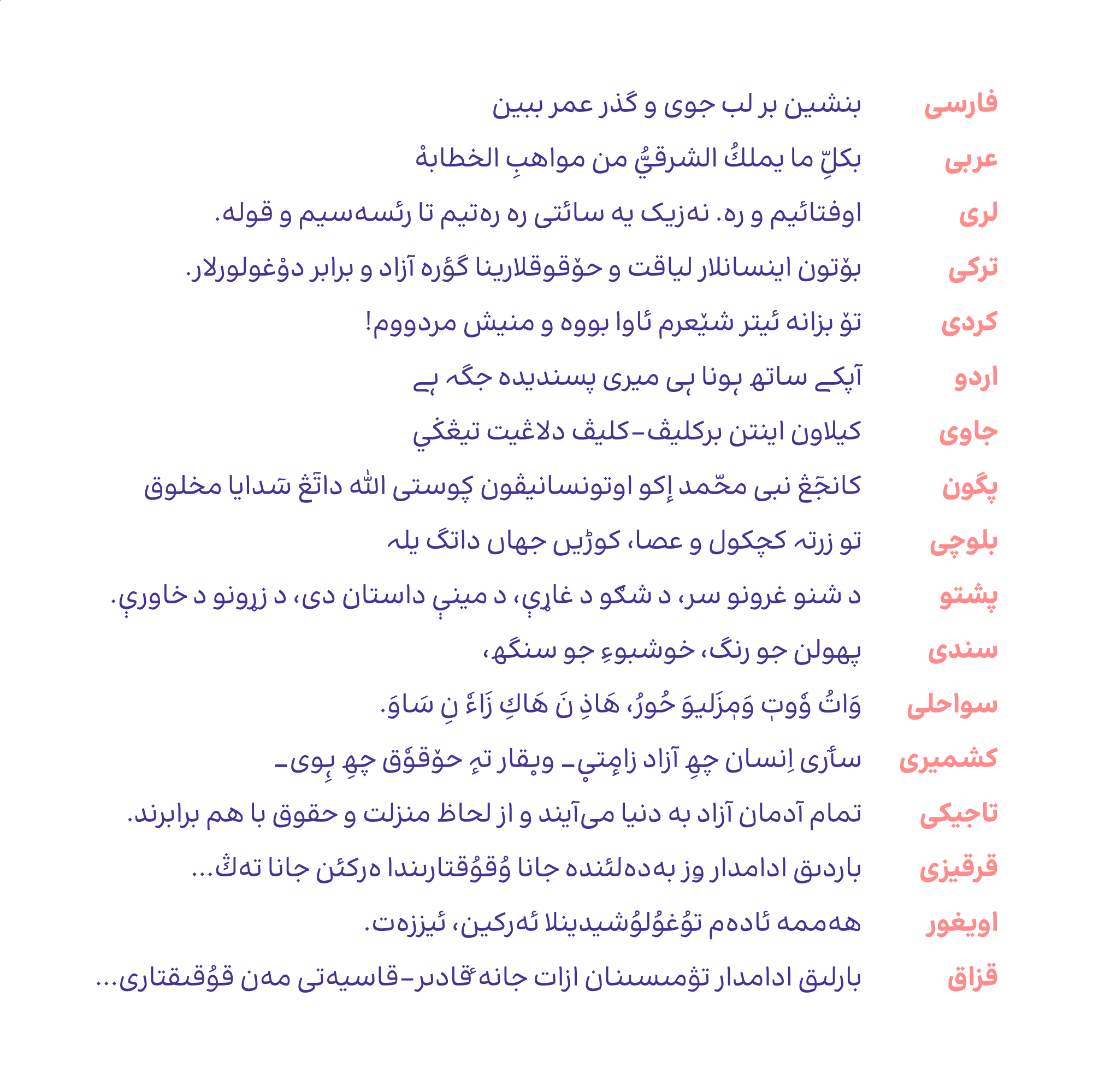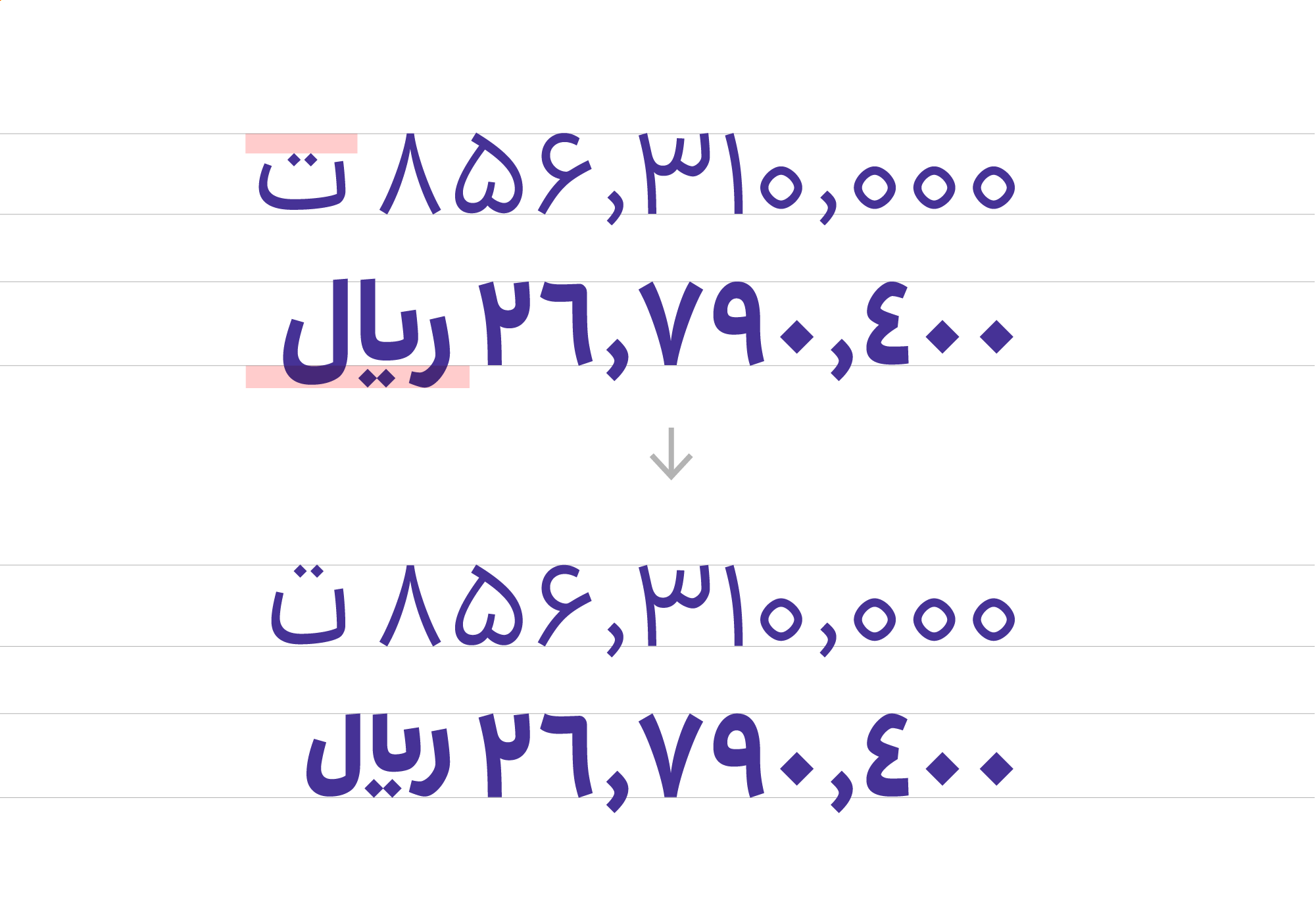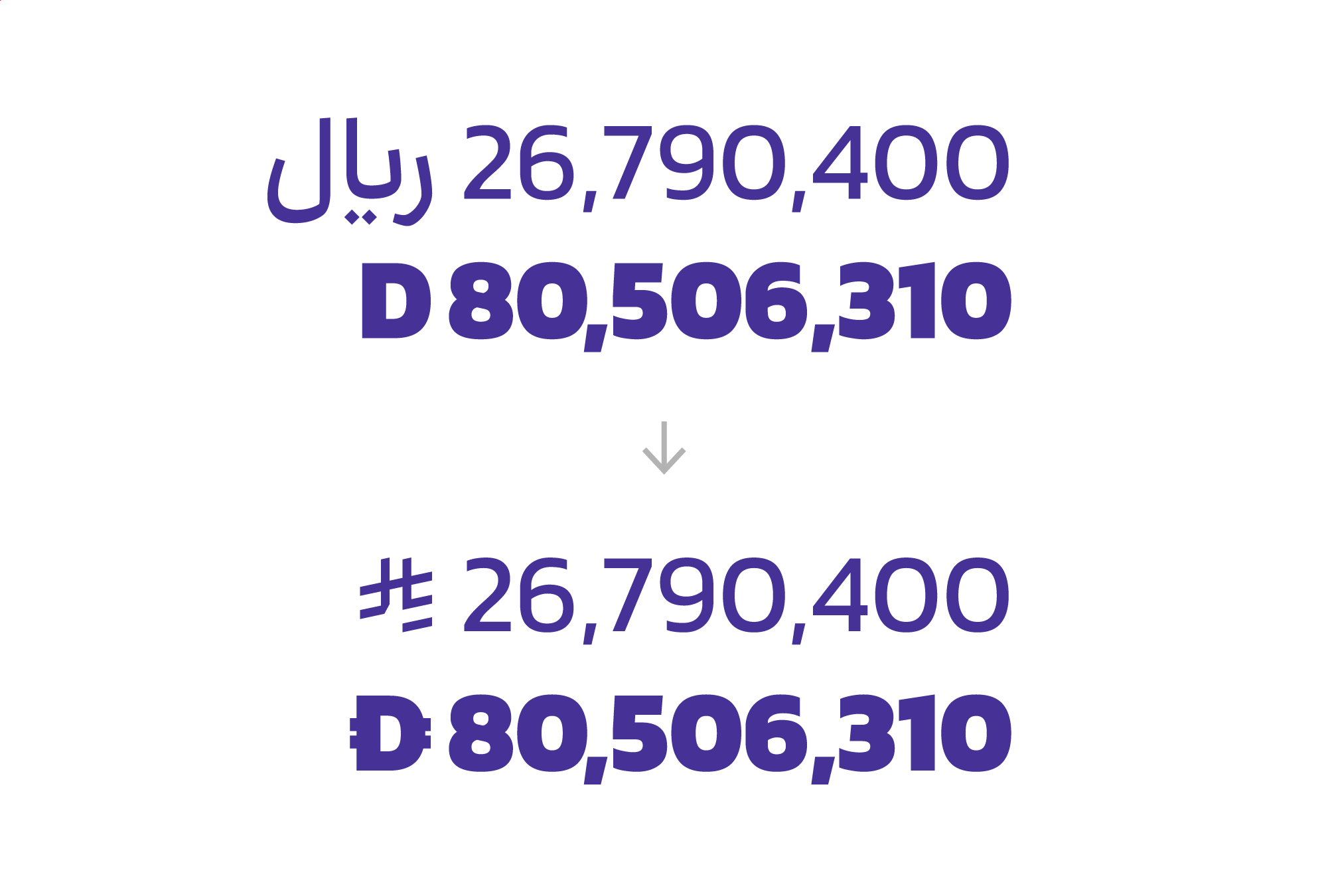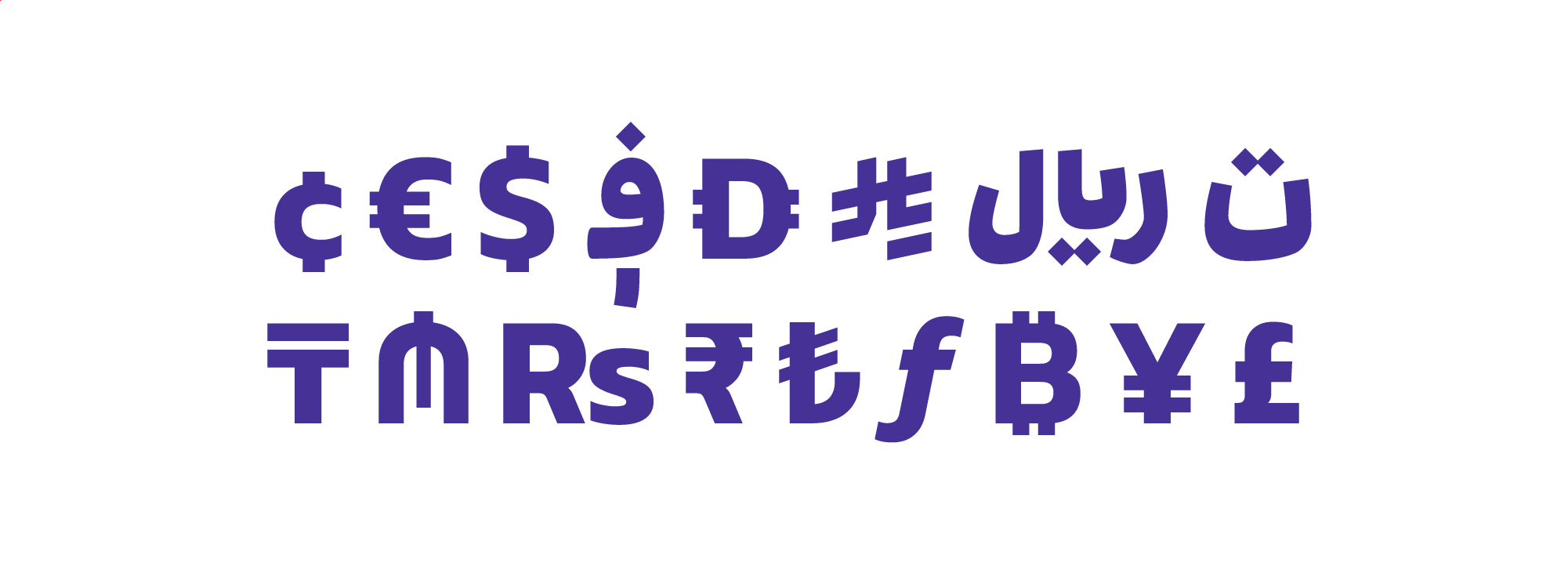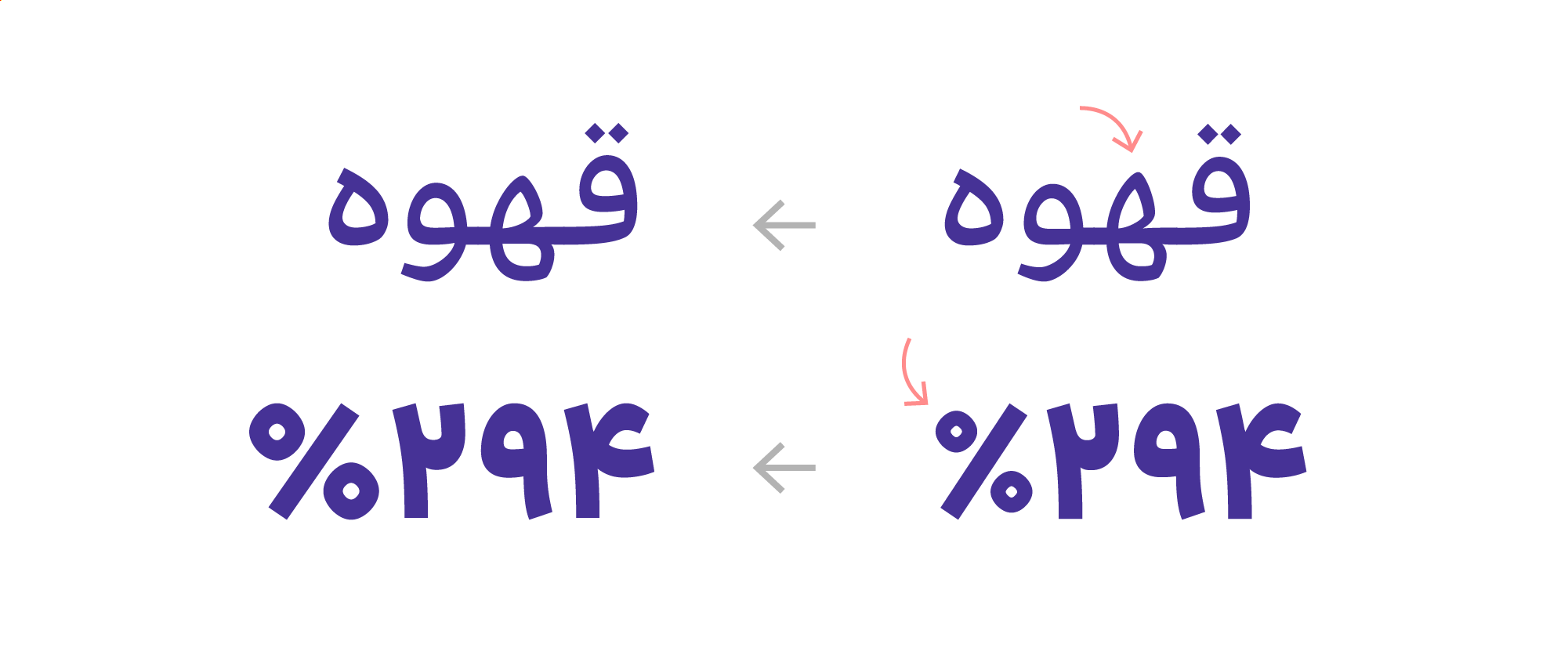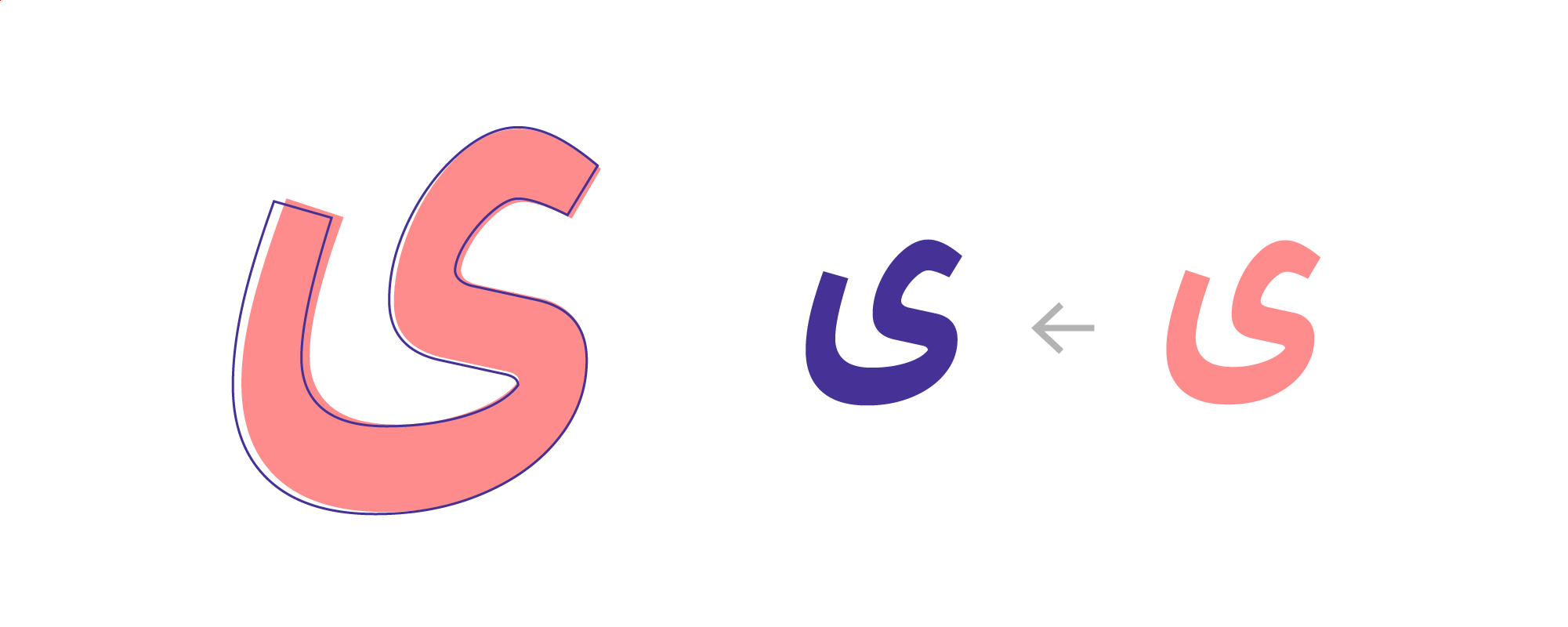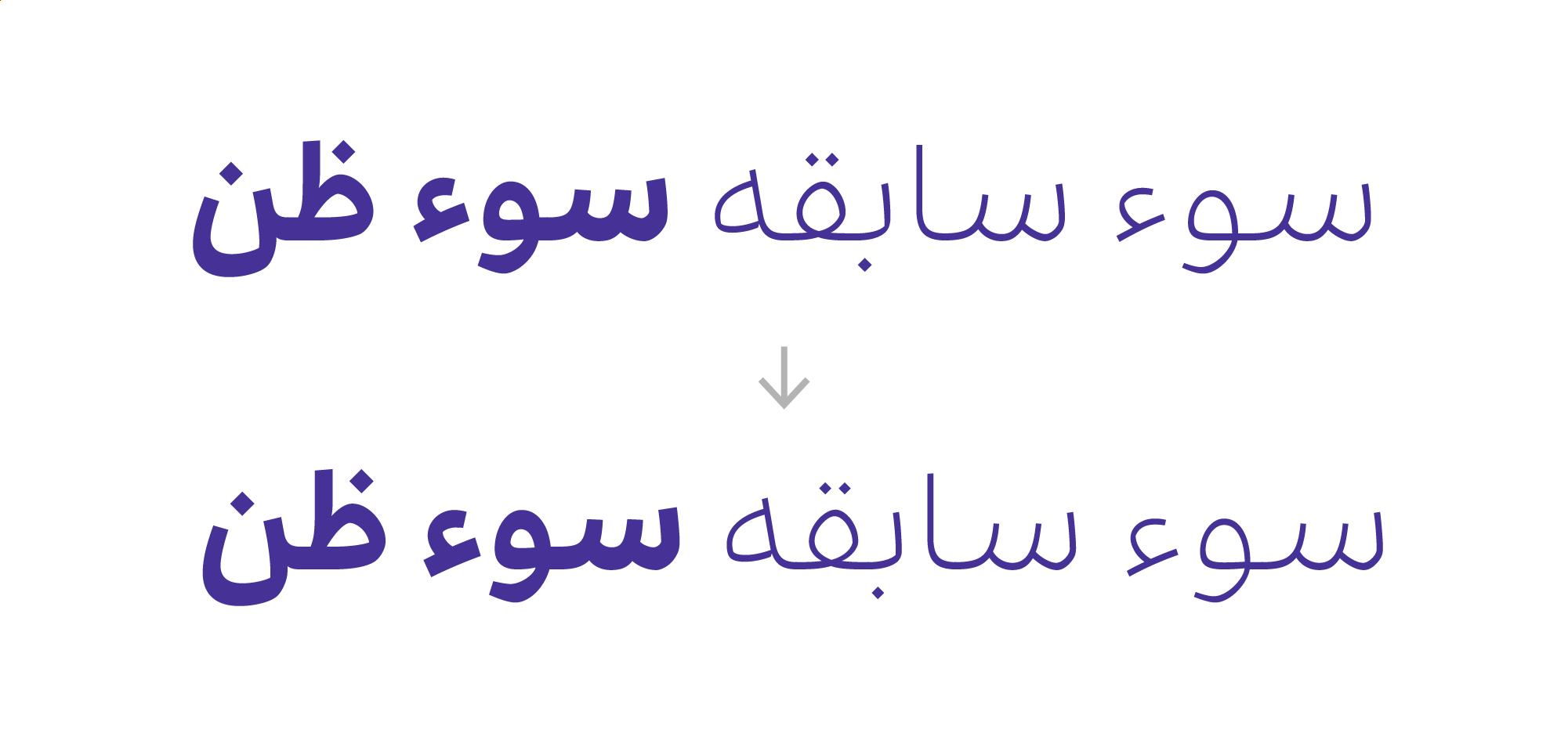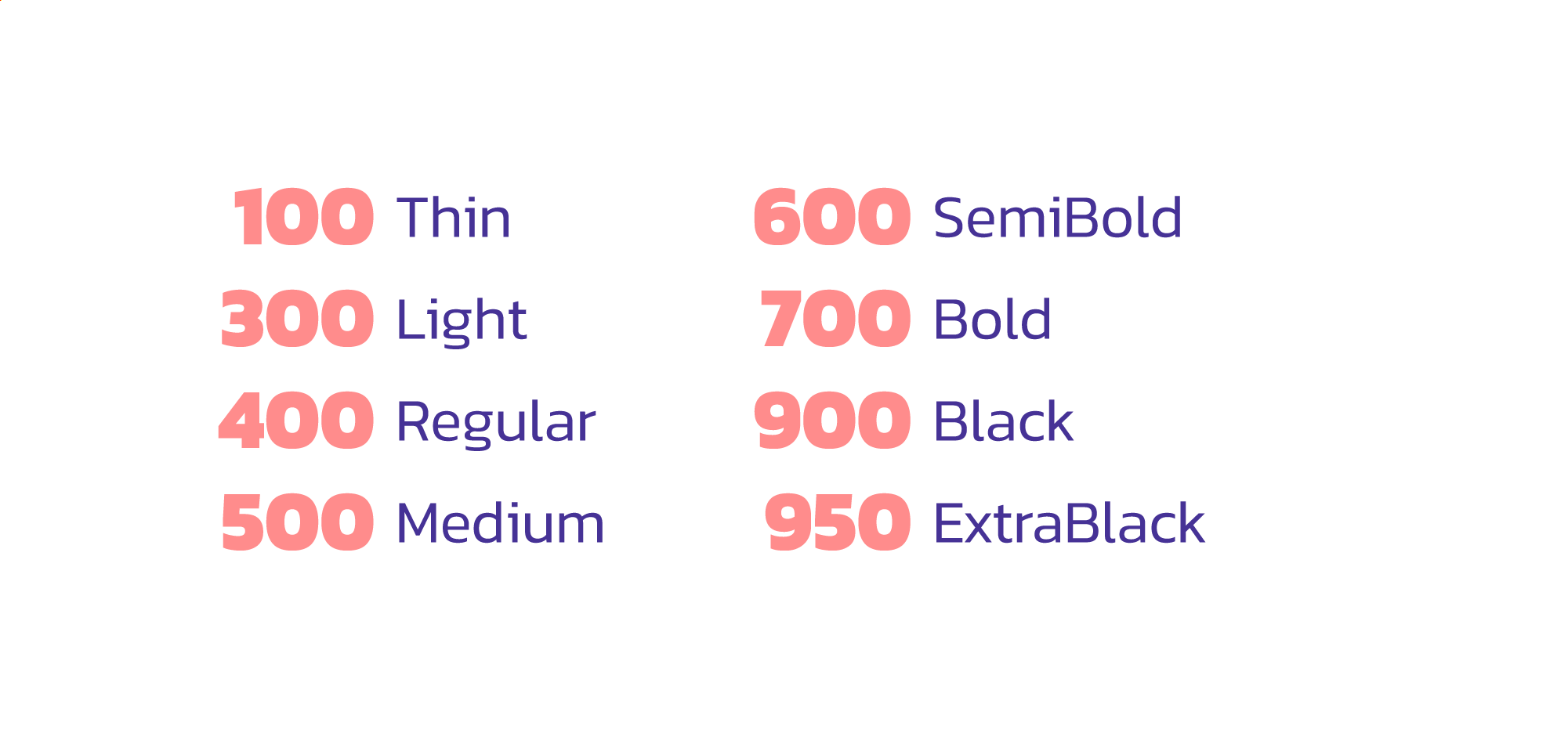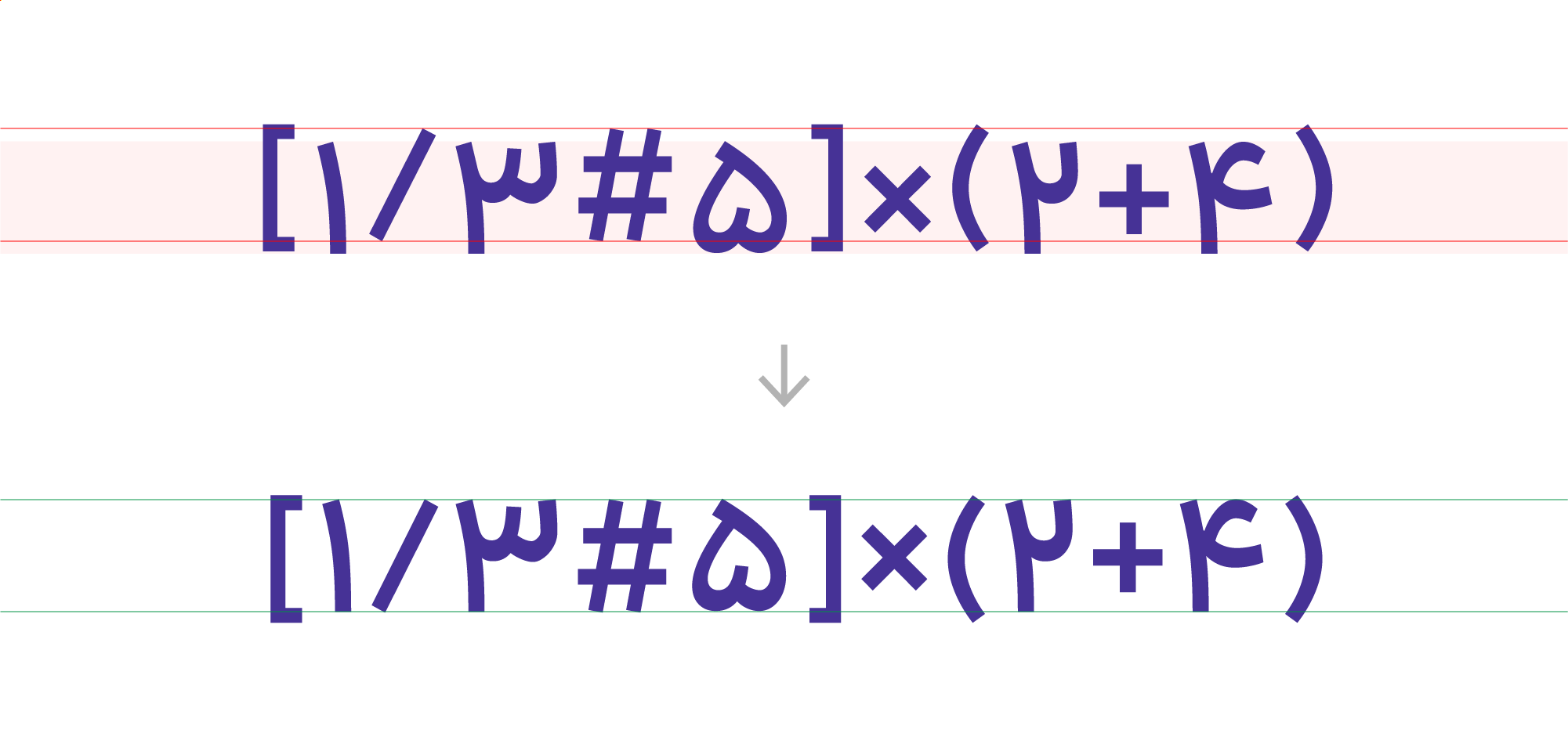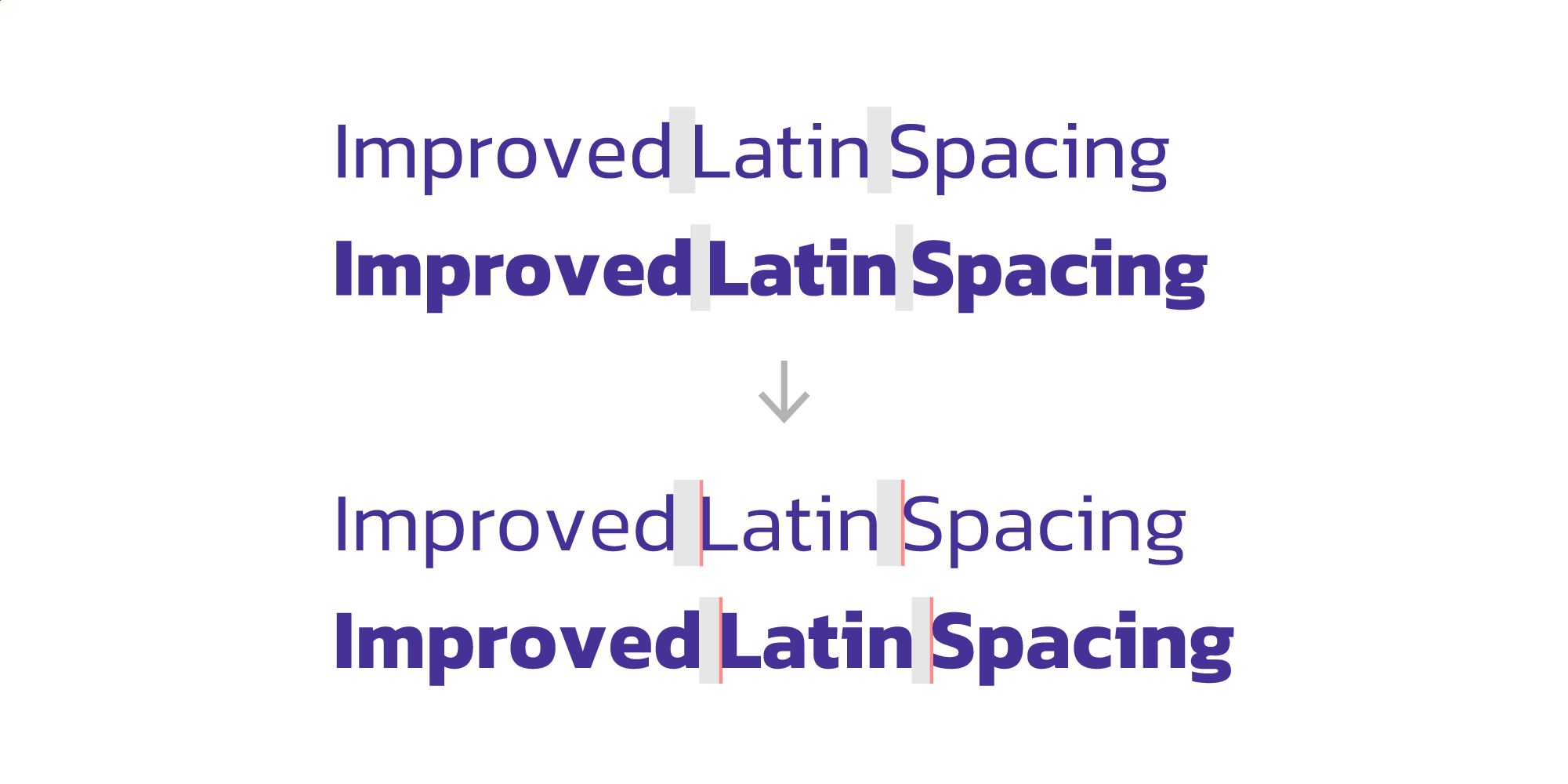
در نسخهی ۲٫۵ فونت راوی چه تغییراتی میبینیم؟
۱. کاراکترهای مربوط به تعدادی از زبانهای زیرمجموعهی فارسی و عربی طراحی شد و حالا فونت از زبانهای زیر پشتیبانی میکند: فارسی، عربی، لری، ترکی، کردی، اردو، جاوی، پگون، بلوچی، پشتو، سندی، کشمیری، تاجیکی، سواحلی، قرقیز، اویغور، قزاق و انگلیسی.
۲. نمادهای «ریال، تومان، ریال عربستان، درهم» طراحی شد.
۳. ده نماد واحد پولی به فونت اضافه شد. حالا فونت جمعا ۱۷ واحد پولی را پوشش میدهد و در ۷۵ کشور قابل استفاده است: تومان، ریال، ریال عربستان، درهم، ؋، $، €، ¢، £، ¥، ₿، ƒ، ₺، ₹، ₨، ₼، ₸.
۴. فرم کاراکترها بازبینی و اصلاح شد.
۵. اندازه، ضخامت و جای «ء» اصلاح شد.
۶. ضخامتها بازبینی و وزنها همآهنگتر شد و مختصات وزنها در فونت وریبل اصلاح، و با حالت استاندارد همآهنگ شد.
۷. با فعال کردن Stylistic Sets 4 تراز عمودی علائم ؟!٪؍٬٫/\⁄'#(){}[]|¦ با حروف همآهنگ میشود.
۸. فاصلهی بین واژهها در زبان انگلیسی بهمنظور خوانایی بیشتر افزایش پیدا کرد.
۹. فرم ه در الله اصلاح شد.
۱۰. مشکل اعرابهای لله و الله برطرف شد. حالا فقط حرف آخر اعراب میگیرد.
۱۱. نماد Tilde به فونت اضافه شد.
۱۲. مشکل جا افتادن نقطه در لیگچرهایی که در آن «ێ» وجود دارد اصلاح شد.
۱۳. فرم کاراکتر Kaf DotAbove مربوط به زبان جاوی اصلاح شد و از «ک» به «ك» تبدیل شد.
۱۴. ضخامت و جای Underline و Strikethrough تنظیم شد.
۱۵. به دلیل عدم یکپارچگی پلتفرمهای مختلف در ساپورت کرنینگ اعداد و ایجاد مشکلات، حذف شدند.